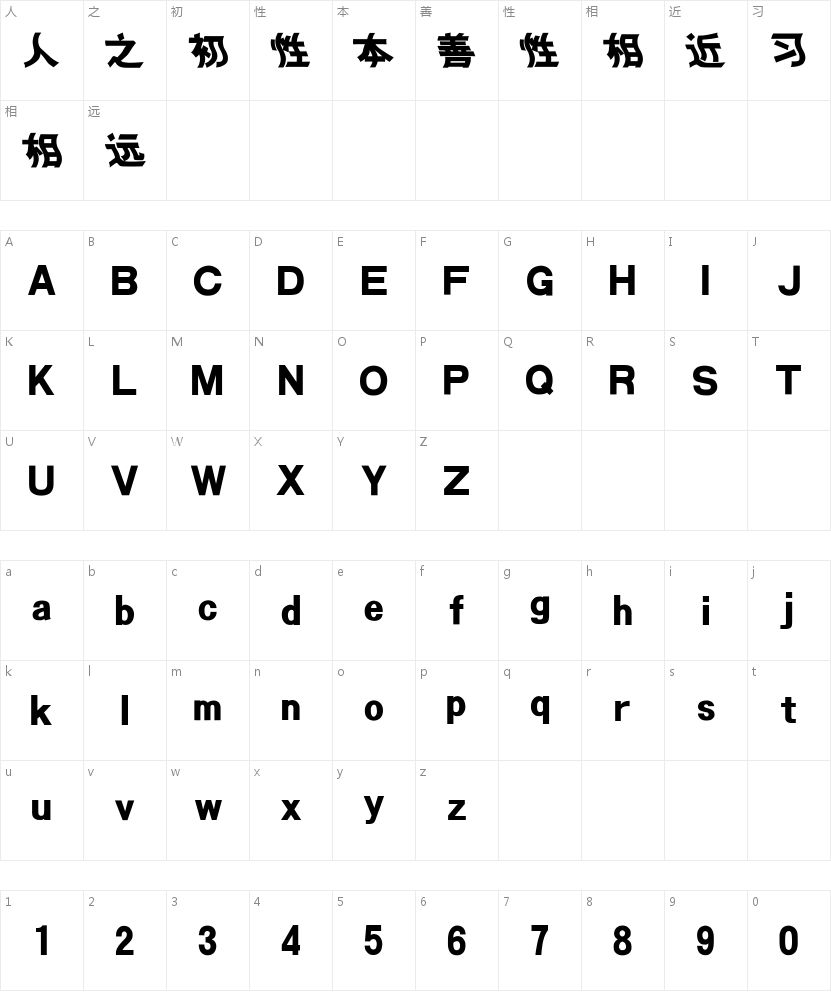
汉仪水波体简是一款汉字字体,其特点是字形仿佛水波荡漾,非常具有动感和流畅感。该字体适用于广告、海报、标语、书籍装帧等多种印刷设计,能够为设计作品增加独特的视觉效果。 该字体的设计灵感来源于中国传统的水墨画和书法艺术,采用了传统的线条结构和笔画特征,但是通过要素的抽象和变形,使其更具现代感和时尚感。字体采用了有机的曲线和流畅的线条,使得每个字形都像是水面上的波纹一样生动而富有变化。 汉仪水波体简包括了常规字体和粗体两种,每种字体都包括了大写字母、小写字母、数字、标点符号和常用汉字,满足了不同设计需求。该字体在中文排版领域具有一定的知名度和使用率,是一款非常优秀的中文字体。文件名:HanYiShuiBoTiJian-1.ttf
汉仪水波体简是一款非常不错的手写艺术字体,具有很好的视觉感,适合于文化类的宣传设计、商业类品牌的广告和产品包装设计以及个性化文字排版等较多场景。